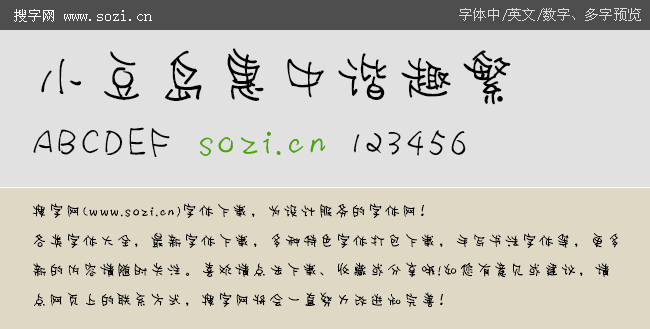
小豆島惠中諧趣繁
搜字網(wǎng)提供一款小豆島惠中諧趣繁中文字體下載,該字體結(jié)構(gòu)整體為傾斜的特點,通過正統(tǒng)書法筆畫間架的解構(gòu),制造一種重心傾斜的視覺感,筆畫活潑,字體筆畫簡單稚拙,寬細(xì)一致,充分體現(xiàn)出活潑諧趣的特點。適合應(yīng)用于廣告設(shè)計、名片設(shè)計、包裝印刷、產(chǎn)品設(shè)計等應(yīng)用。